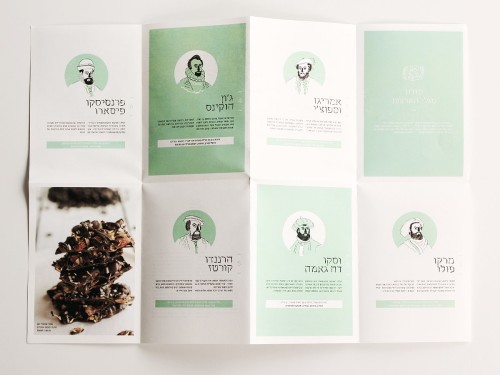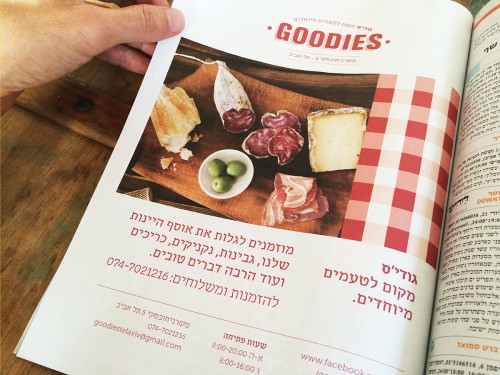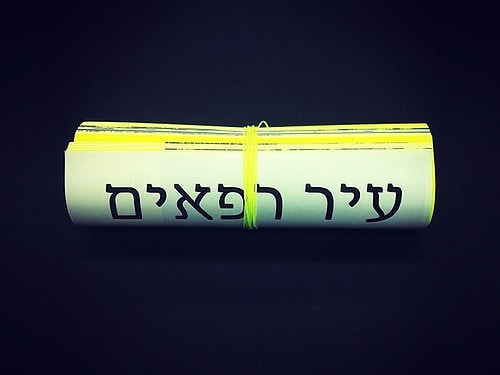
על אודות פונט מקומי
מקומי שואב את השראתו הצורנית משורשי האות של הגופן הקלאסי פרנק־ריהל. הוא נועד לכותרות מרעננות ולטקסט־רץ קריא וזורם. זה גופן יציב ובטוח, ומנגד ספונטני ומשוחרר. הוא כולל חמישה משקלים וכך ניתן להשתמש בו ביסודיות ובגמישות.
תהליך העיצוב והפיתוח — שארך שנים רבות — כלל בדיקות דקדקניות ממושכות. שלד הגופן נבנה על גבי גריד פיקסלים בטכניקה חופשית שהובילה לגילוי שלל צורות חדשות של האות העברית. הגופן הושק בגרסתו הראשונה ב־2011, ומאז המשיך להתפתח עד לגרסתו הנוכחית, הדו־לשונית, שהושקה בסוף 2017.
החליפו את הטקסט־הרץ שלכם בגופן מפתיע, סריפי וקריא.
המלצת שימוש לפי משקל
לייט לכותרות בגודל 24 pt ומעלה
רגיל, בינוני ובולד לטקסט־רץ סריפי קריא וזורם וגם לכותרות אלגנטיות
אולטרה־בולד לכותרות בגודל 20 pt ומעלה -
ליגטורות סטנדרטיות
ליגטורות סודיות
- חלופות הקשריות gj ← gj
מספרים וסימנים
- שברים, מוֹנֶה וְמְכַנֶּה 1/3 ← 1/3
- מספרים סִדּוּרִיים May 21st ← May 21st
- מספרים טבלאיים 1,234.00% ← 1,234.00%
- חלופות סגנוניות g ← g
- סוואשים (סה״כ 17) איציק ← איציק